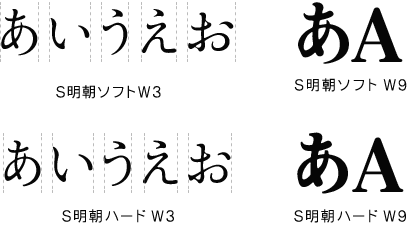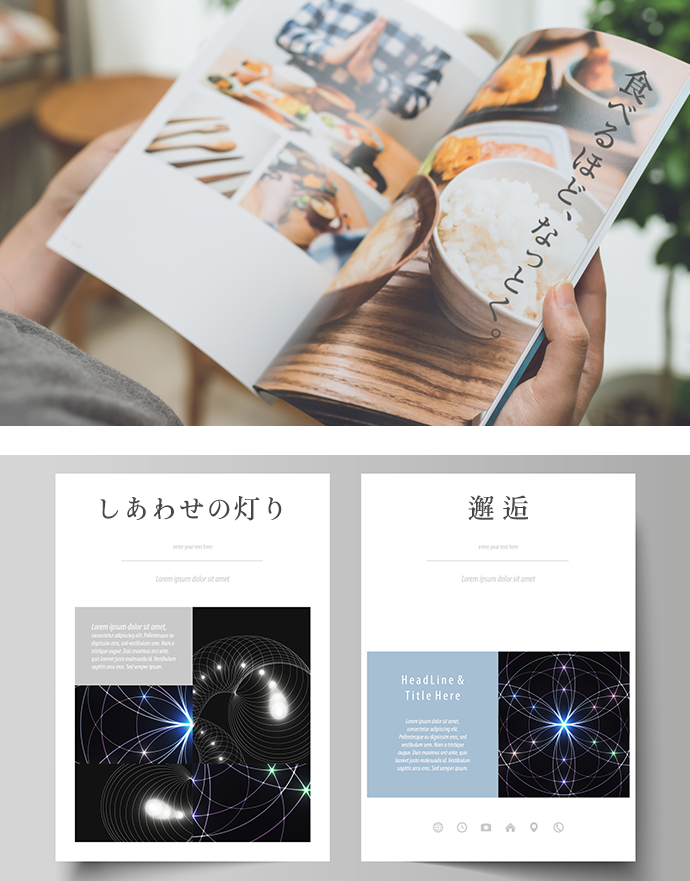
S明朝シリーズ
「柔らかなイメージと自然さ」をコンセプトにしたベーシックなフォルムです。文字の運びとかたちを大切にしているため、キャッチフレーズからボディコピー、エディトリアルなど、広告・雑誌、デザインをはじめ、幅広い分野でお使いいただけます。
主な特長
S明朝シリーズには大きく分けて「ソフト」と「ハード」タイプの2デザインをご用意。
ソフトのひらがな・カタカナは、筆の運びとかたちを大切にしているため、ひとつひとつの文字幅が違います
ハードは逆にひらがな・カタカナのひとつひとつの文字幅を近づけて、ボディコピーで組んだ時の自然なリズムを意識
一番太いW9は「活字」を意識しています。インパクトのあるタイトルやキャッチフレーズ向きです。
開発背景
設計当初は、パソコンで使用する日本文字に硬さがあり表現力も低かったものの、パソコン自体の性能が上がることによって文字のかたちやディテールにもこだわれる環境になってきました。広告クリエイターでもあった開発者が、デザイン制作時でも既成のフォントでは飽き足らず、レベルの高いタイポグラフィーを実現したいという想いから企画されたのが「S明朝シリーズ」です。
活用事例
キャッチフレーズなど明確なものからエディトリアルまで幅広くお使いいただけます。
作家紹介 関征春
子供の頃から書道に興味を持ち続け、書海社(書道の谷村喜斎)の上段を持ち、特に楷書を中心に研究しています。ひらがな・カタカナは日本の歴史のある「かたち」のカーブを大切にしてきました。筆から自然に生まれる要素と可読性を重要視し、奇をてらうのではなく次代へ繋いでいける文字をモットーとしています。コーポレートアイデンティティが騒がれた時には有名な企業、ブランドのロゴタイプも手がけています。